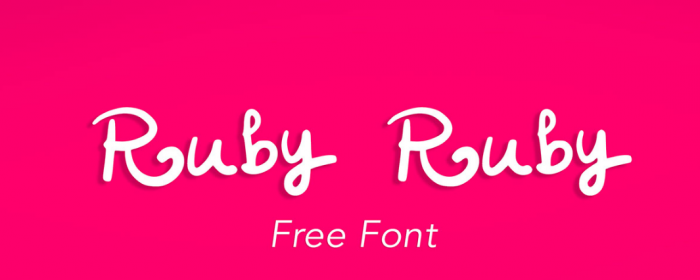
Ruby Ruby : retournez en enfance avec cette typographie gratuite
Typographie : Ruby Ruby
La typographie Ruby Ruby est d’inspiration infantile et faite à la main, ce qui la rend parfaite pour des créations décontractées, sur des flyers par exemple.